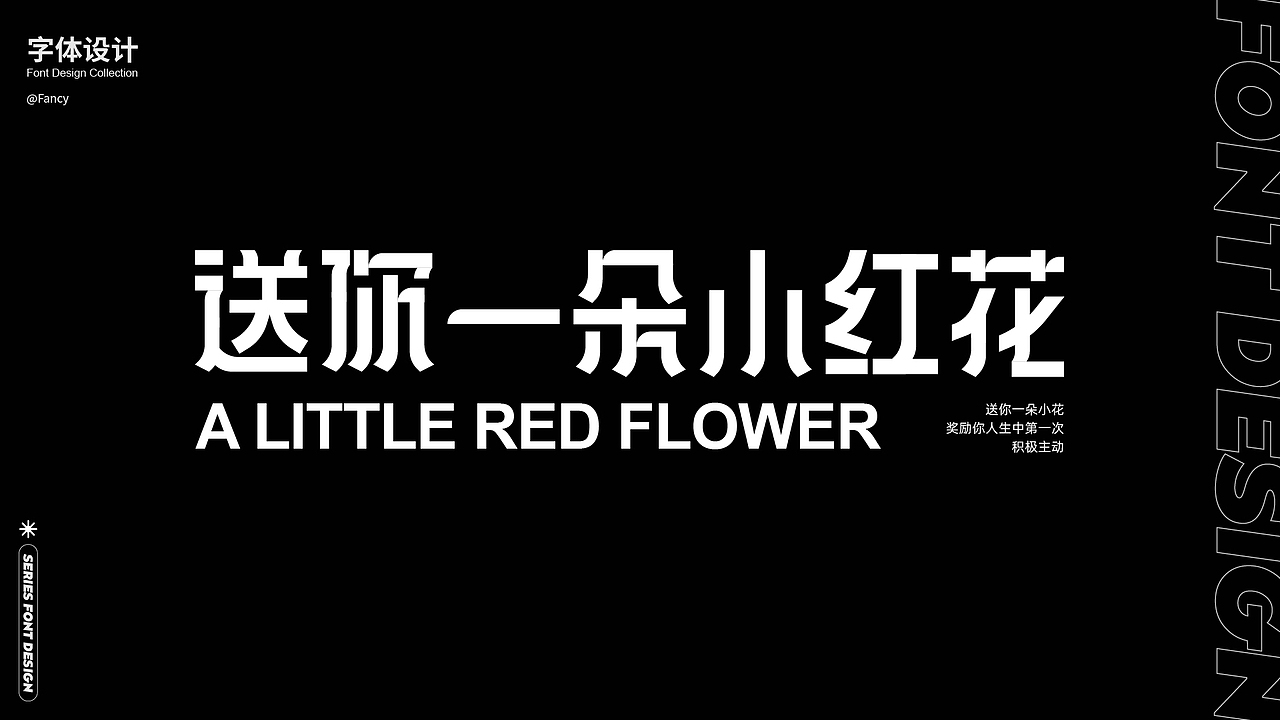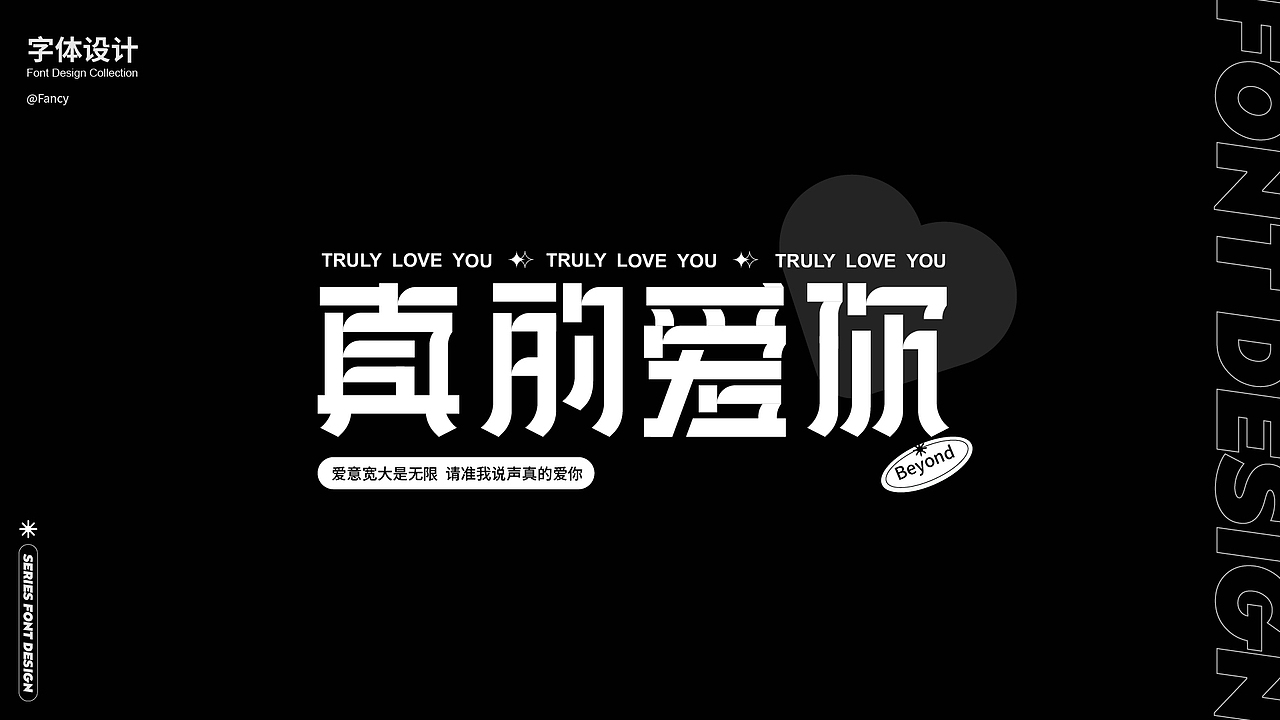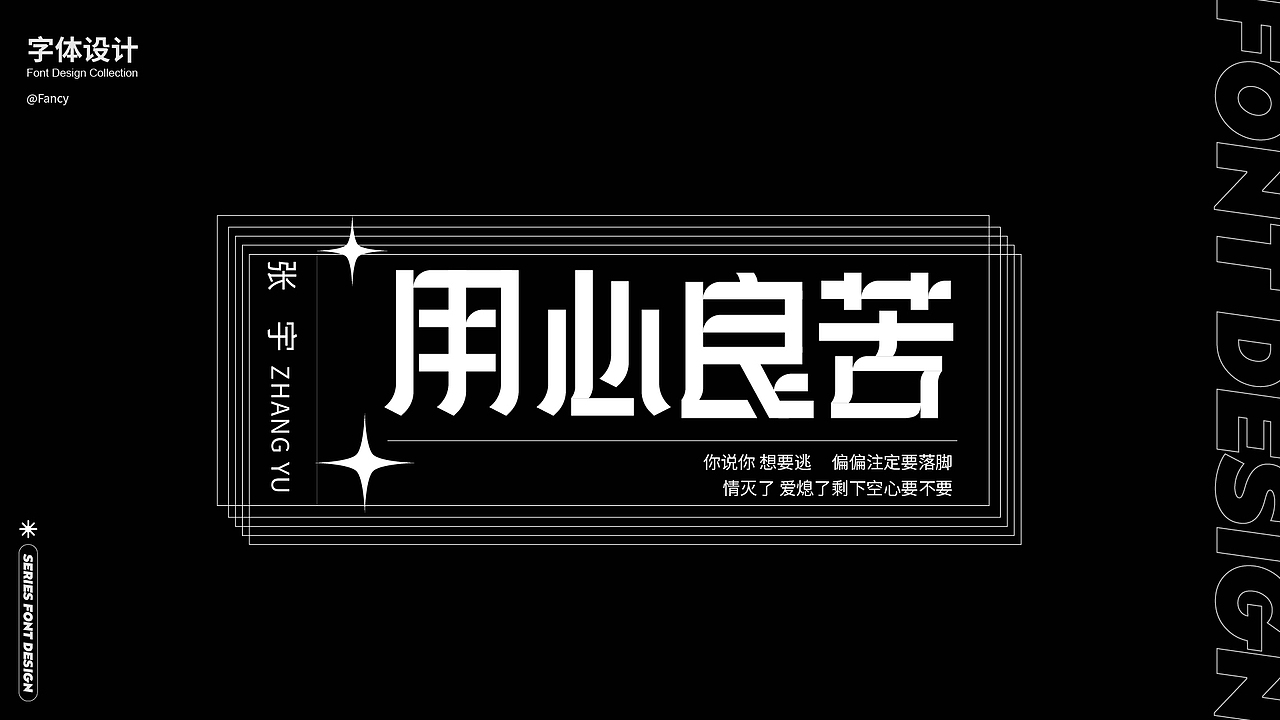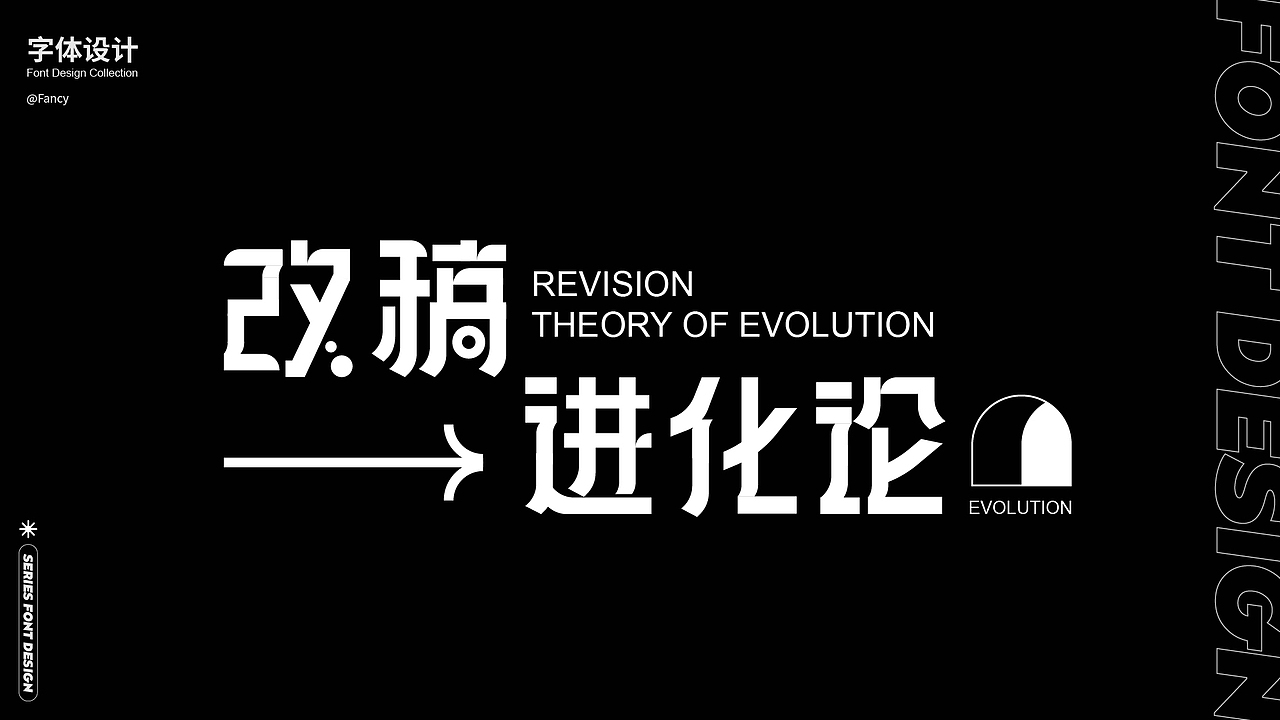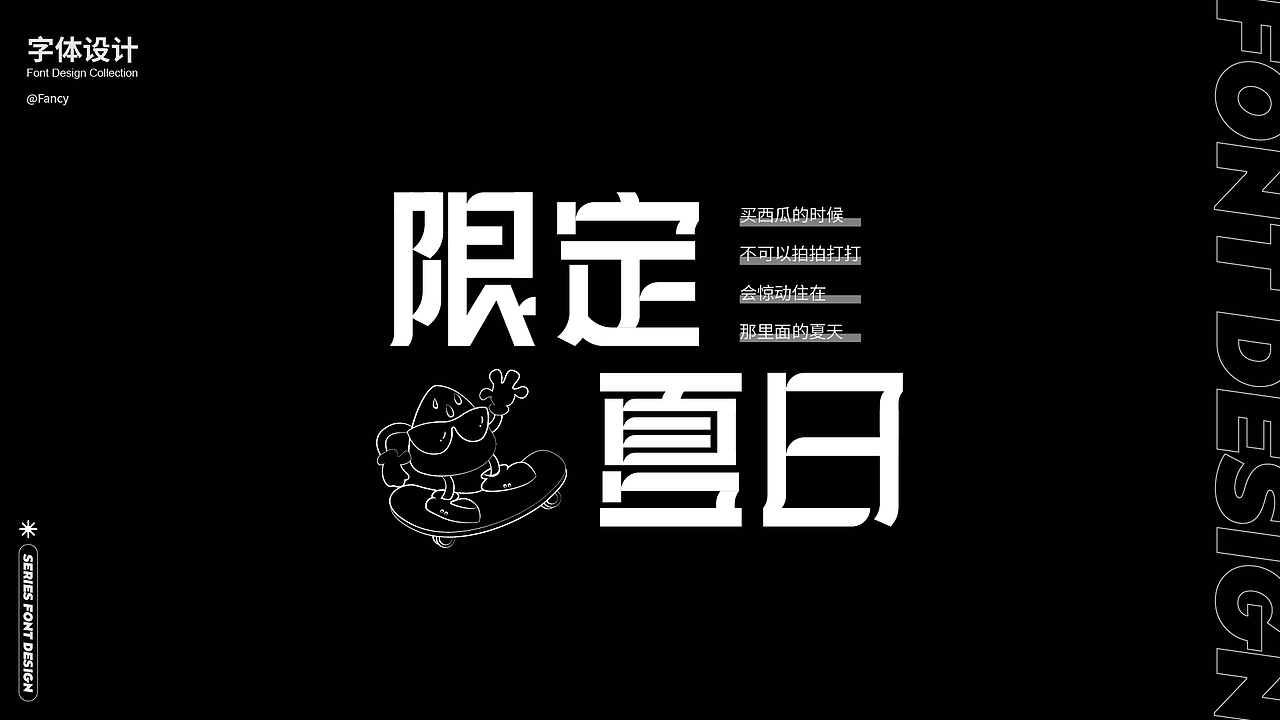
抽空整合归类一组字体设计
这组字体整体采用的稍微硬朗一点的字体设计,
但同时笔画细节处有曲线和圆角处理,方中带圆,硬中有柔,刚柔并济~
在字体设计的过程中,其实跟我们的生活经历很相似,
我们每个人生活都会经历各种酸甜苦辣,
但是不管处于什么境遇,
尤其是正处于生活困难模式的话,
请记得要微笑面对它
保持良好心态,尽全力在不愉快的日子里搜刮生活藏下的所有温柔;
保持热爱,总会有很多瞬间告诉你,生活温柔且浪漫;对待热爱的事情都要不遗余力。